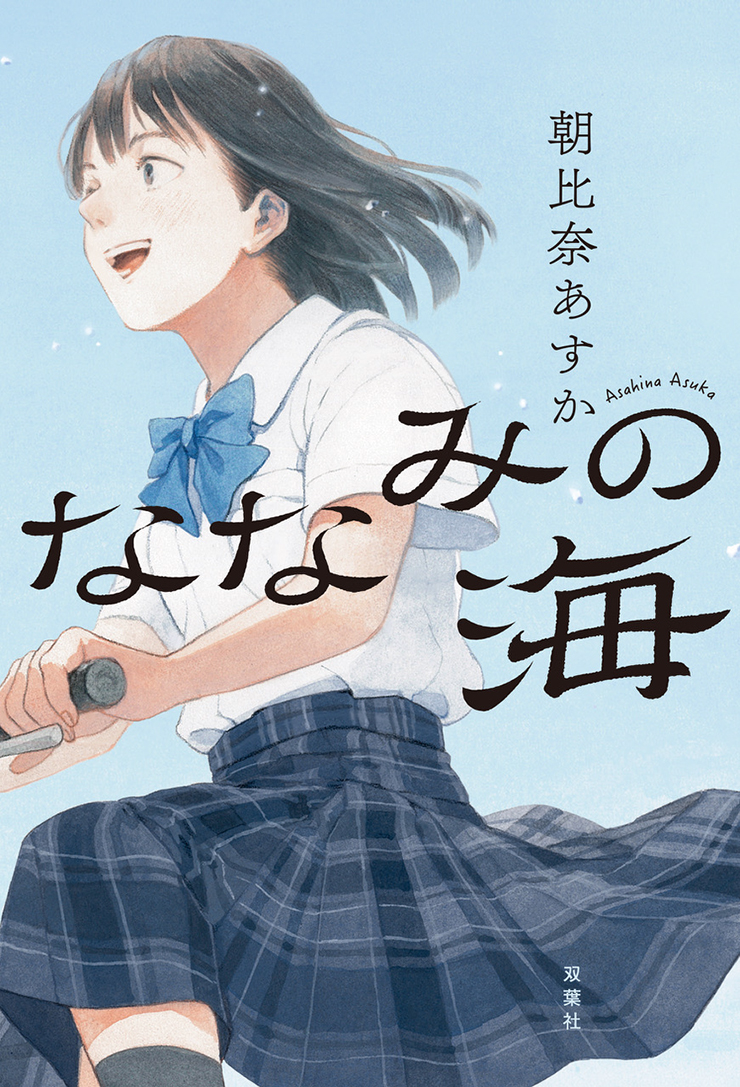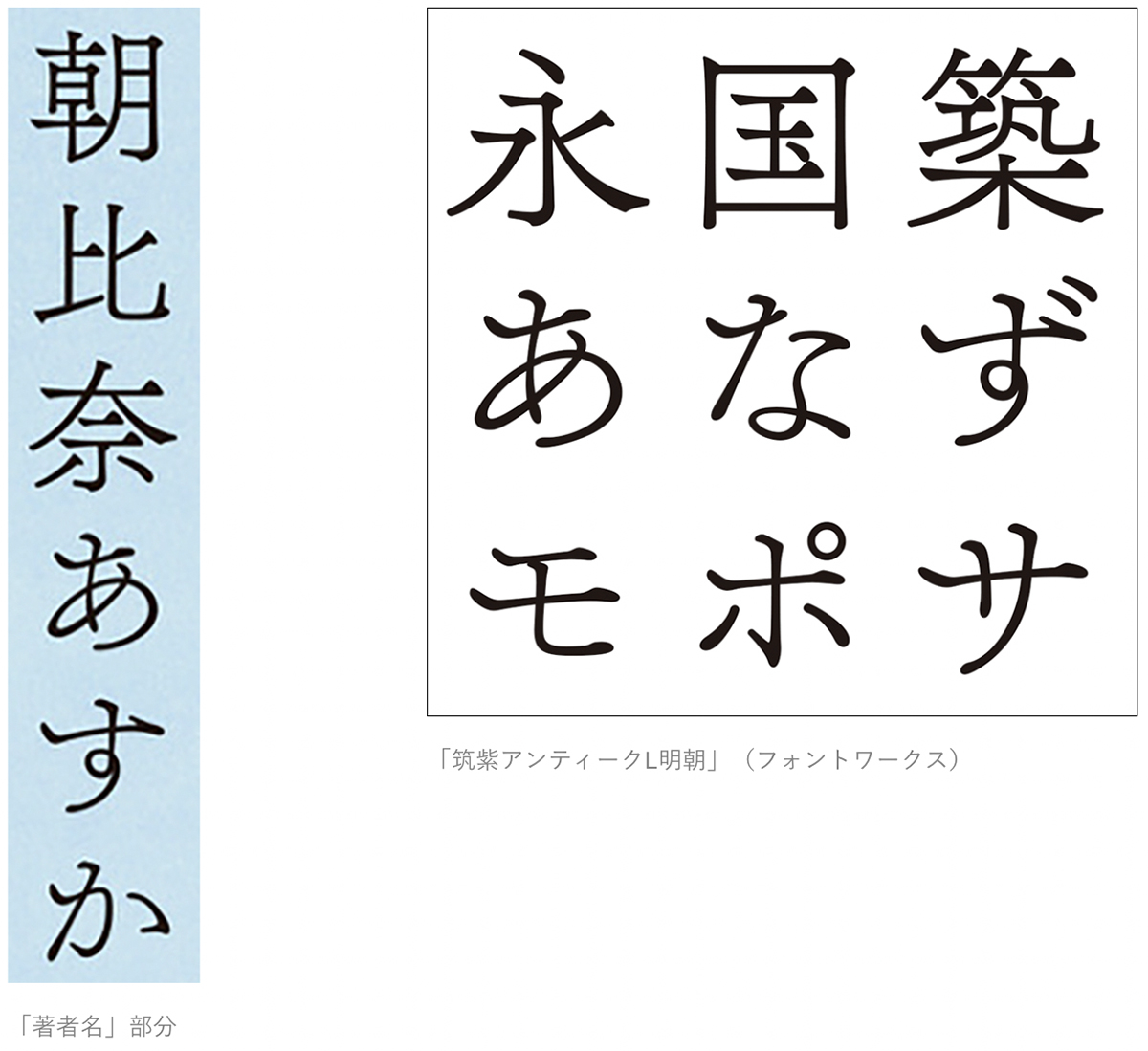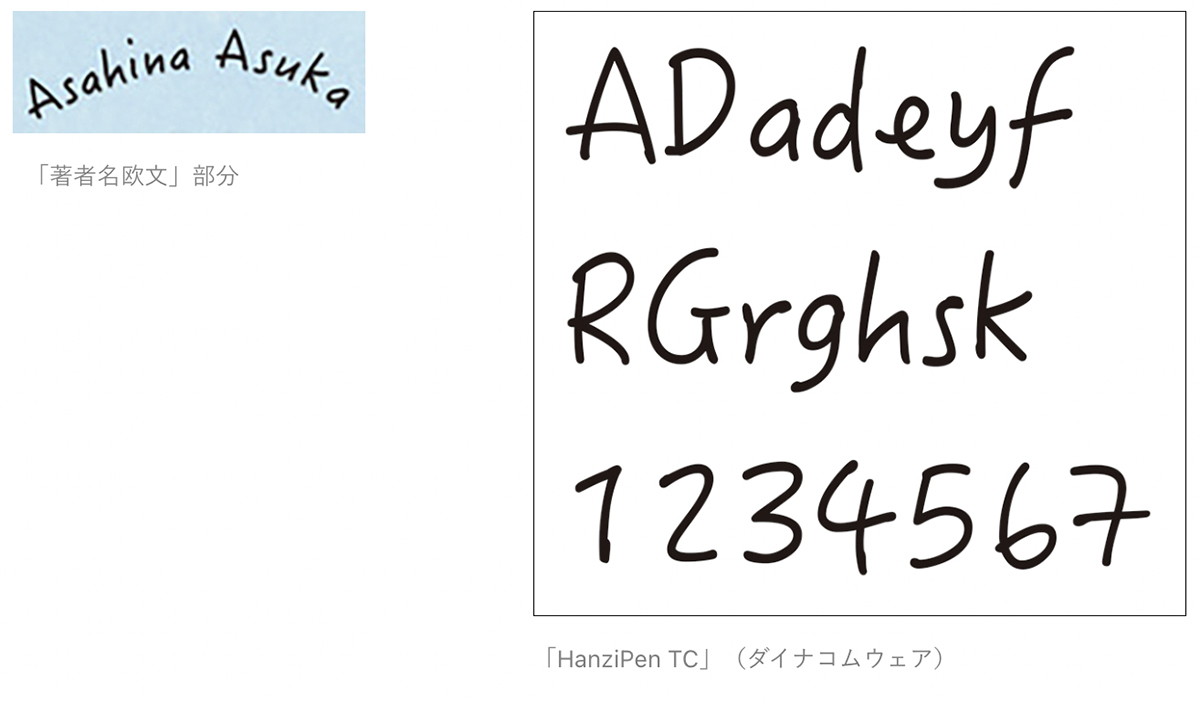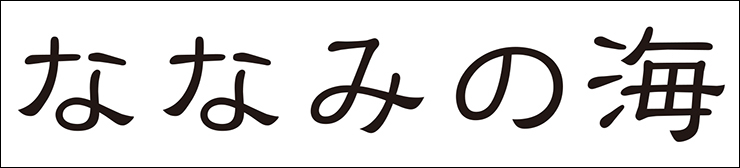
今回は書籍『ななみの海/朝比奈あすか』(双葉社)の使用フォントを解説。ブックデザインを手がけた草苅睦子[アルビレオ]さんに取材しました。
海の波をイメージした文字で十代の心許なさや揺らぎを爽やかに表現
児童養護施設で暮らす高校生のななみが、受験勉強やアルバイト、部活、学校や施設での人間関係などを通して成長していく姿を描いた青春小説『ななみの海/朝比奈あすか』。施設という環境にいるからこそ直面する葛藤を掘り下げながらも、十代の普遍的な悩みや日常が生き生きと丁寧に書き込まれており、世代を問わず共感できる内容になっています。
表紙カバーでは、その十代の心許なさや揺らぎ、主人公の少女の成長や青春が、眩しいほどの輝きを感じさせるイラストや、海の波をイメージしたタイトルロゴなどで印象的に表現されています。デザインを担当した草苅さんによると「表紙カバーでは、作品の爽やかな世界観を大切に表現するよう心がけました。当初は主人公と同世代の読者を念頭にもう少しポップなタイトルロゴを考えていたのですが、大人も共感できる普遍性のある成長物語なので、より幅広い世代の読者が手に取りやすいようなデザインにしました」とのことです。
Font.01「オリジナル(陸隷)」
海の波をイメージした文字で優しく爽やかな印象に
メインタイトルの文字は、伝統的でありながらモダンな表情も併せ持つ隷書体「陸隷」(モリサワ)をベースに作り起こされたオリジナルのもの。海の波のイメージに合わせて平体をかけたり、ハライの形状を変えたりしながら制作されました。
草苅さんによれば「穏やかで優しく包み込んでくれるような、それでいて凛とした力強さもある海の波をイメージしています。元の書体からは大きく形を変えていますが、波のイメージを表現しつつも、隷書体が持つ端正な雰囲気は壊さないよう心がけました」とのこと。
Font.02「筑紫アンティークL明朝」
作品の優しい雰囲気に合わせて風情豊かな明朝体に
著者名部分の文字は、金属活字を思わせる古典的で風情豊かな「筑紫アンティークL明朝」(フォントワークス)に。草苅さんによれば「作品のイメージに合わせて優しく爽やかな感じにしたかったので、ゴシック体ではなく明朝系の書体を検討しました。ただ、オーソドックスな明朝体だと隷書体をベースにしたタイトルロゴとバッティングしてしまいそうだったので、フトコロが狭く伸びやかな書体を選んで差別化しています」とのこと。
Font.03「HanziPen TC」
手書き風の文字で若々しく可愛らしく
著者名の欧文部分の文字は、ペンで書いたような手書き風書体「HanziPen TC」(ダイナコムウェア)に。中国語の繁体字用書体の従属欧文だが、作品の若々しい雰囲気にピッタリだったため選択されました。
草苅さんによれば「十代の少女の成長を描いた作品なので、どこかに可愛らしい要素を加えてアクセントをつけたいと考えて、いろいろ書体を試してみたのですが、いちばんしっくりきたのがこの書体でした。著者名の和文書体とのバランスにも配慮しつつ、主人公のななみちゃんが書いたようなイメージで選びました」とのことです。